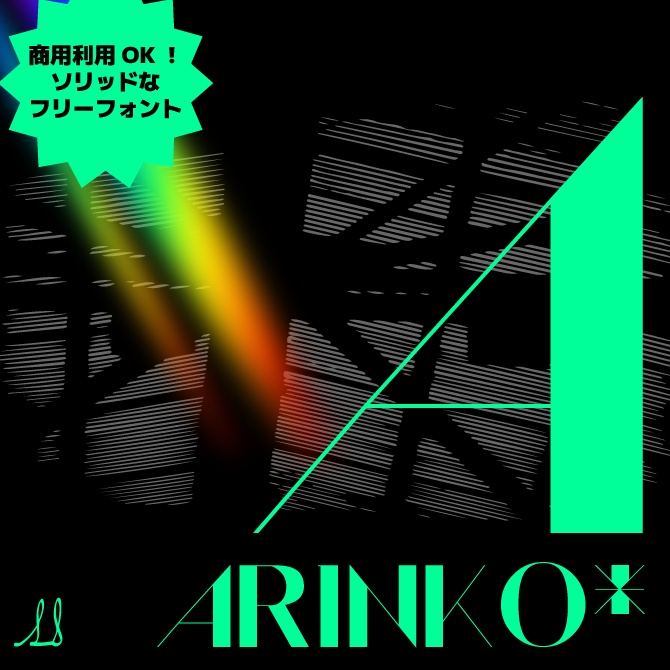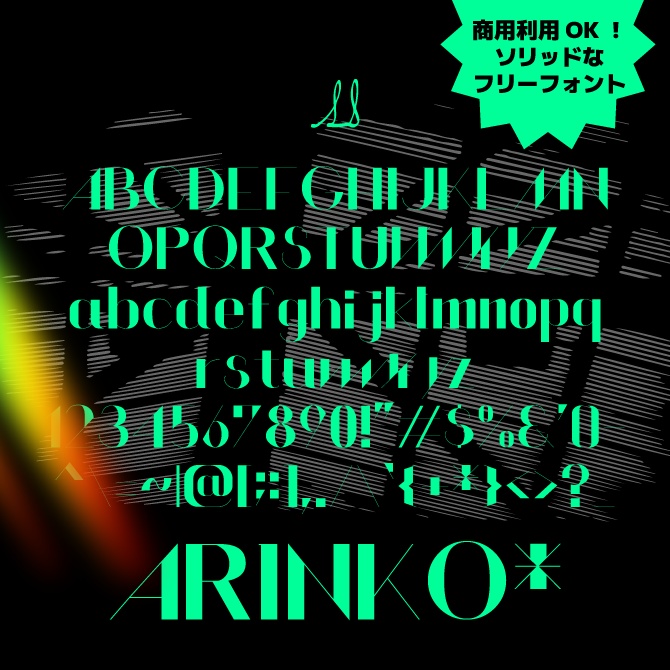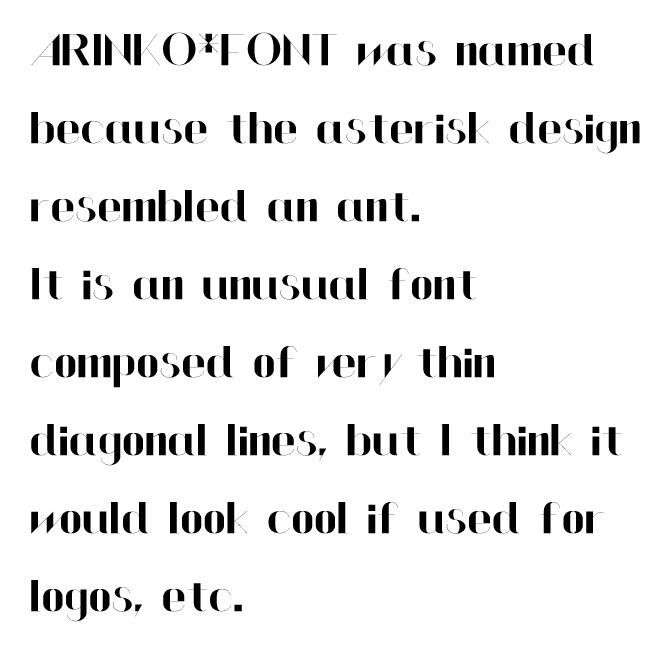
アスタリスクのデザインがありんこに見えたことから名づけることになったARINKO*FONT。 極細の斜めラインで構成された風変わりなフォントですが、ロゴなどにお使いいただくと格好いいと思います。 ARINKO*FONT was named because the asterisk design resembled an ant. It is an unusual font composed of very thin diagonal lines, but I think it would look cool if used for logos, etc.
収録文字
基本ラテン文字、約物、記号類(一部) 合計92字収録